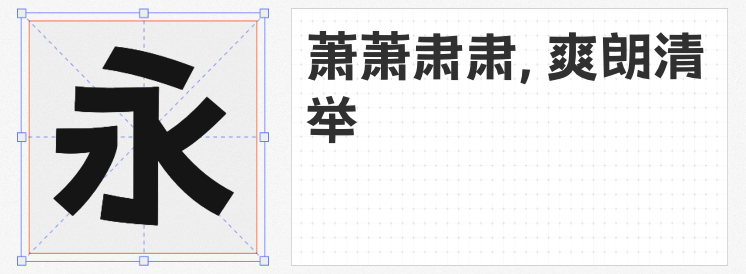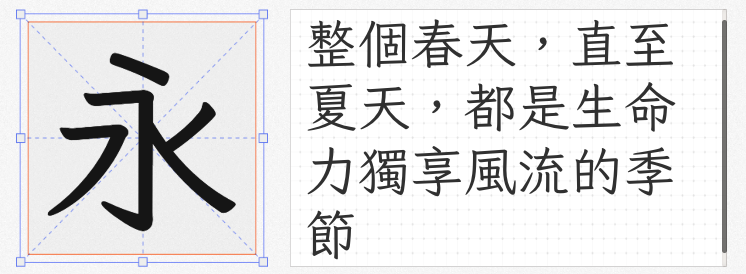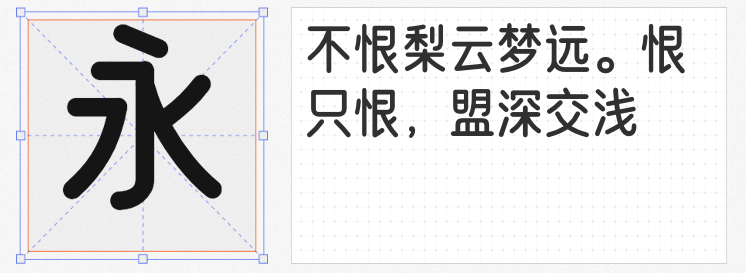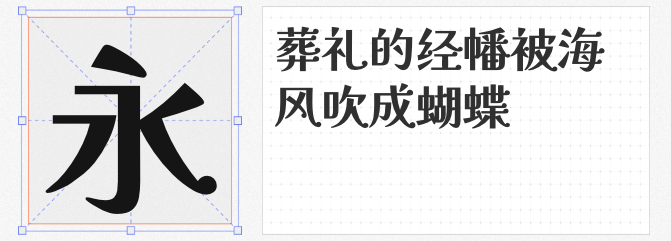
在创意设计领域,字体不仅是信息传递的载体,更是塑造视觉风格的核心元素。然而,商用字体的高昂授权费用常让预算有限的设计师望而却步。以下四款风格迥异、可免费商用的优质字体,以开放授权与专业设计水准,为海报、包装、品牌视觉等场景提供高性价比解决方案。
由设计师 微博@设裂星辰 基于日本开源字体解星体二次创作的这款字体,以棱角分明的几何笔触重构传统书写美学。倾斜的笔画走势与不规则折角处理,赋予文字强烈的未来科技感,同时保留手写的动态韵律。其独特的“破碎感”字形非常适合电竞海报、潮流品牌包装等需要突破常规的视觉场景,开源属性更让年轻创作者得以自由探索字体设计的边界。
针对字体Klee One在中文排版中的缺字问题,“芫荽”字体通过调整字形结构、补充台客语用字,打造出贴近教育标准字体的中文解决方案。柔和的楷体笔调与仿宋的工整性相融合,形成既易读又充满童趣的视觉体验。0.8cm以上的字号能清晰展现笔画细节,使其成为儿童读物、课堂板书、国字习作等场景的理想选择,温暖的外形更易拉近与学龄用户的距离。
来自荆南字坊的这款字体,以流畅的连笔设计与适中的字重,还原了日常书写的自然状态。略带倾斜的笔画走势赋予文字跃动感,而收放自如的笔画粗细变化则强化了视觉层次。无论是社交媒体图文、手账素材还是文艺风海报,都能通过这款字体传递出轻松随性的生活态度,成为平衡专业感与亲和力的绝佳选择。
专为健康主题设计的这款字体,通过纵向拉长的字形结构与硬挺的弧度控制,塑造出兼具轻盈感与稳定性的视觉形态。圆润的基底中融入直线元素,使字体在展现柔美曲线的同时不失现代感。特别适合健身APP界面、营养品包装、运动品牌宣传等需要传递健康理念的设计场景,细节处的硬朗处理更暗含突破自我的运动精神。